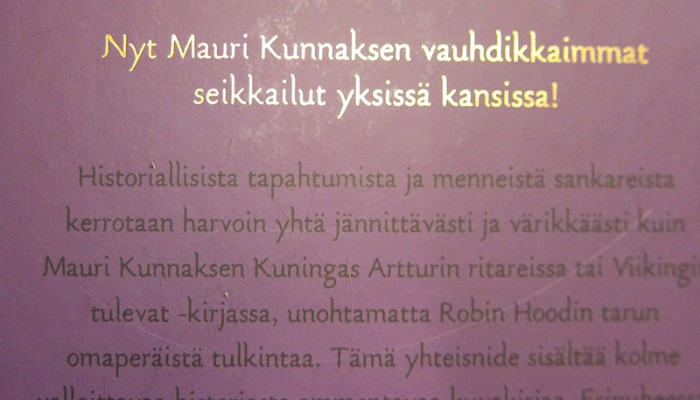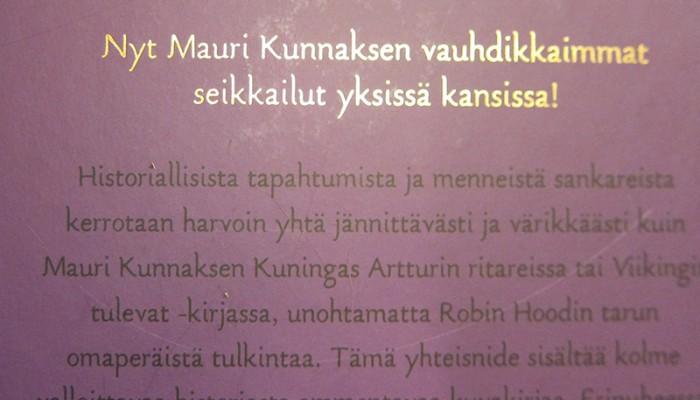
Schrift-Identifikation, Finnisches Kinderbuch
Ich suche folgende Schrift. Das Foto stammt von der Rückseite eines finnischen Kinderbuchs "Mauri Kunnas - Suuret Tarinat" erschienen bei Otava, 2014.
"WhatTheFont" schlägt mir "FF Roice" und "FF Engine" vor.
Besonders die "Engine" ist nah dran und wäre eine gute Alternative, aber es ist nicht die aus dem Bild.
die freundliche grafikerin des finnischen verlags hat innert einer halben stunde geantwortet.
Um der Sache vielleicht einen kleinen Mehrwert hinzuzufügen, aus welcher Richtung ich komme: Ich war auf der Suche nach einer Schrift, die zum einen deutliche historische, nordische bis mythische Bezüge hat, zum anderen aber dennoch moderne Lesbarkeit bietet. Die Gararond bietet die Lesbarkeit, weil sie auf Garamond basiert. Ist aber vielleicht doch etwas zu altbacken.
Underware Fakir kommt in den Sinn, aber die ist mir etwas zu Display und auch zu hip.
Ich glaube nun "Ode" von MartinPlusFonts könnte die richtige Mischung haben. Ich hoffe das hilft jemandem.
Um der Sache vielleicht einen kleinen Mehrwert hinzuzufügen, aus welcher Richtung ich komme: Ich war auf der Suche nach einer Schrift, die zum einen deutliche historische, nordische bis mythische Bezüge hat, zum anderen aber dennoch moderne Lesbarkeit bietet. Die Gararond bietet die Lesbarkeit, weil sie auf Garamond basiert. Ist aber vielleicht doch etwas zu altbacken.